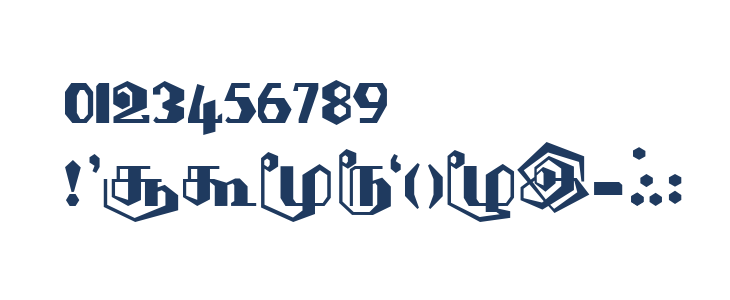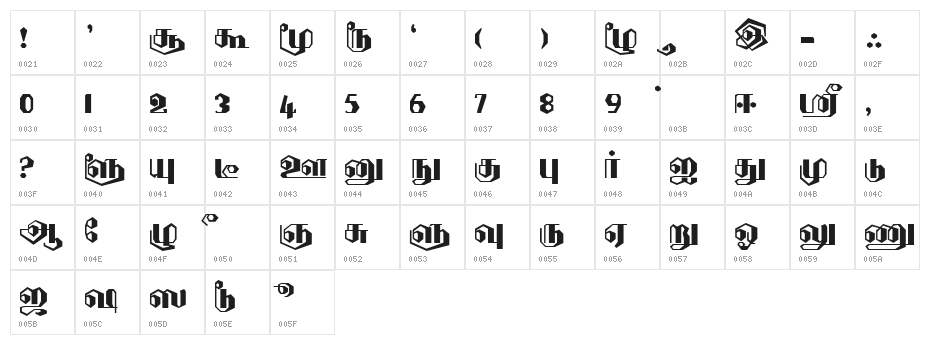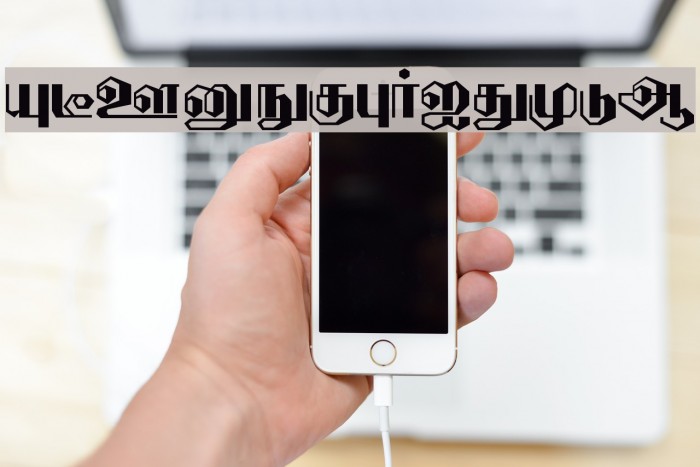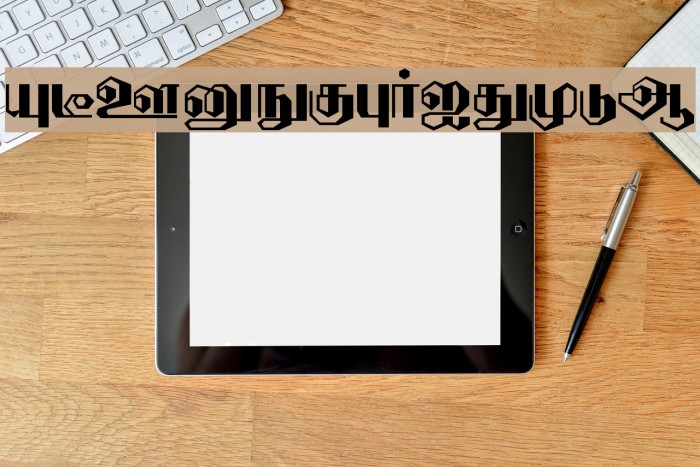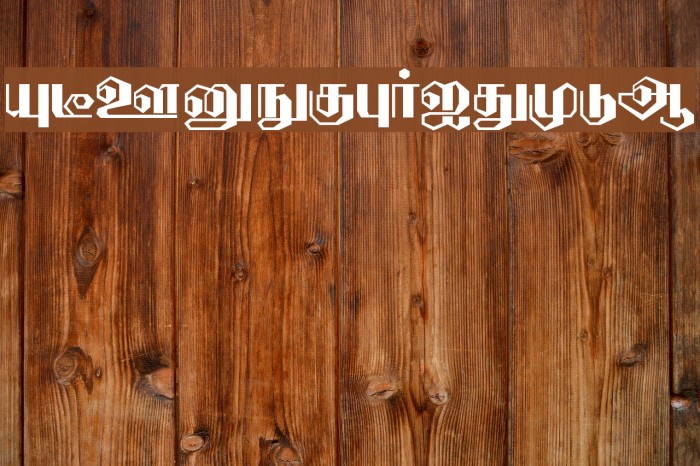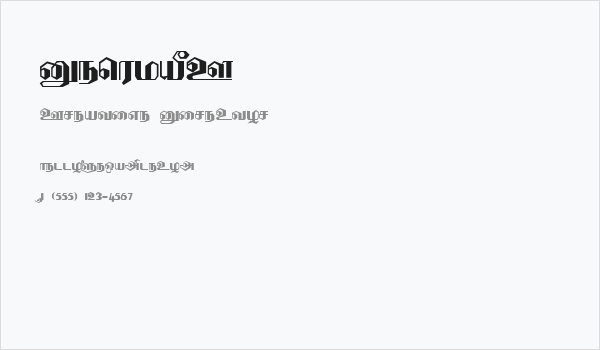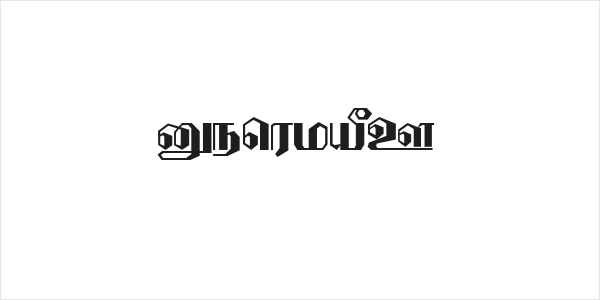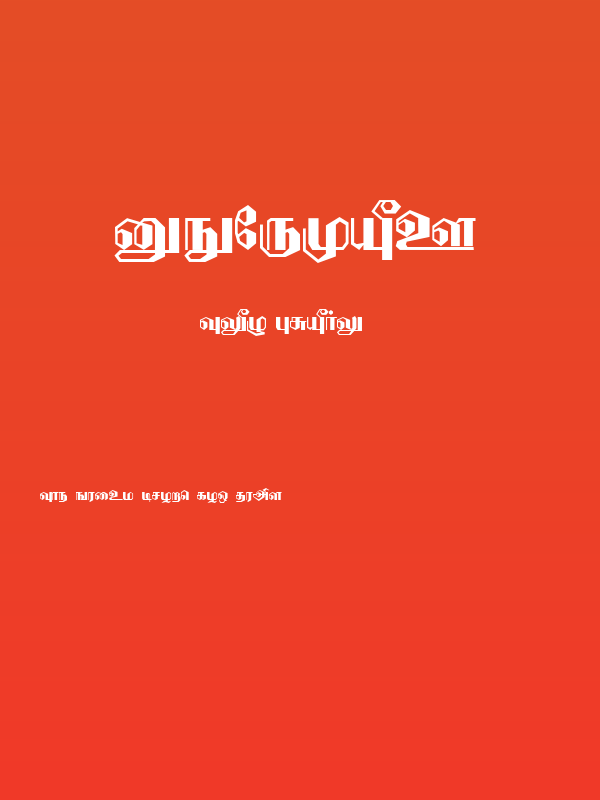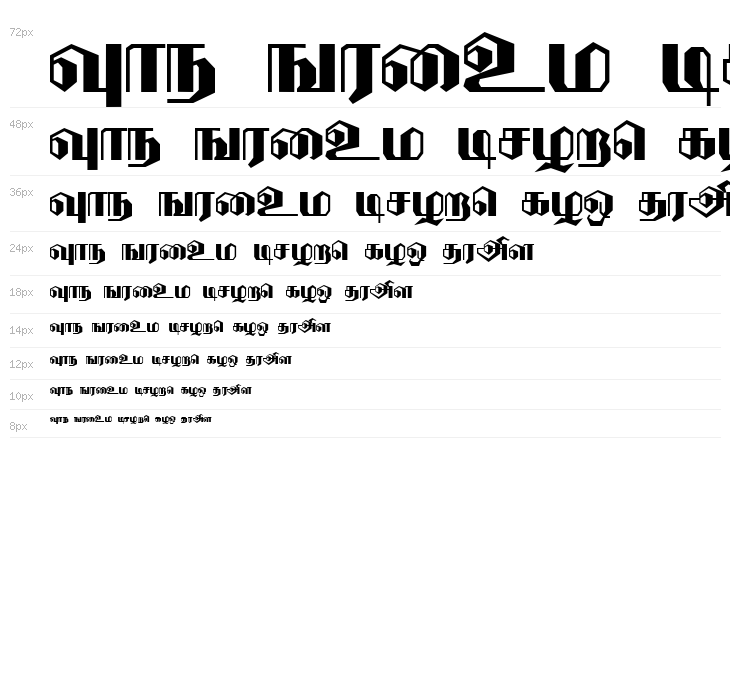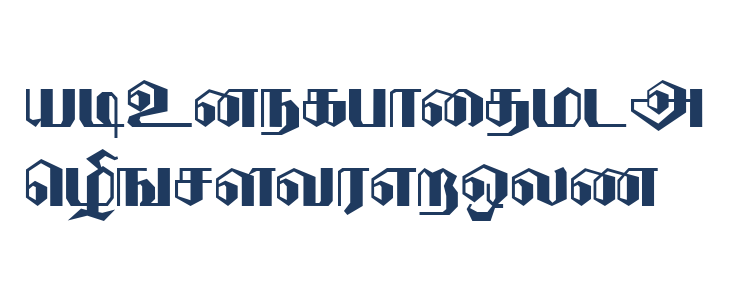
DenukaPC Font
| Vorgeschlagene Projekte | Ideal for posters, logos, headlines, and branding materials that require a bold and authoritative presence. |